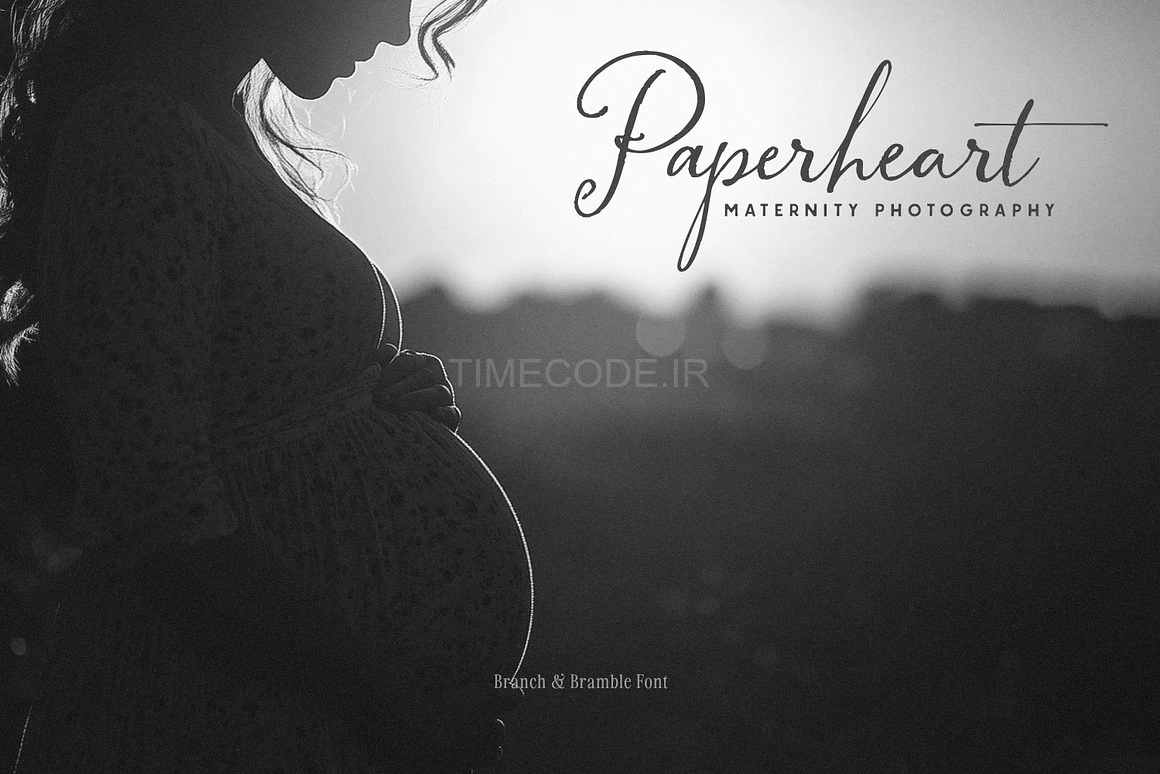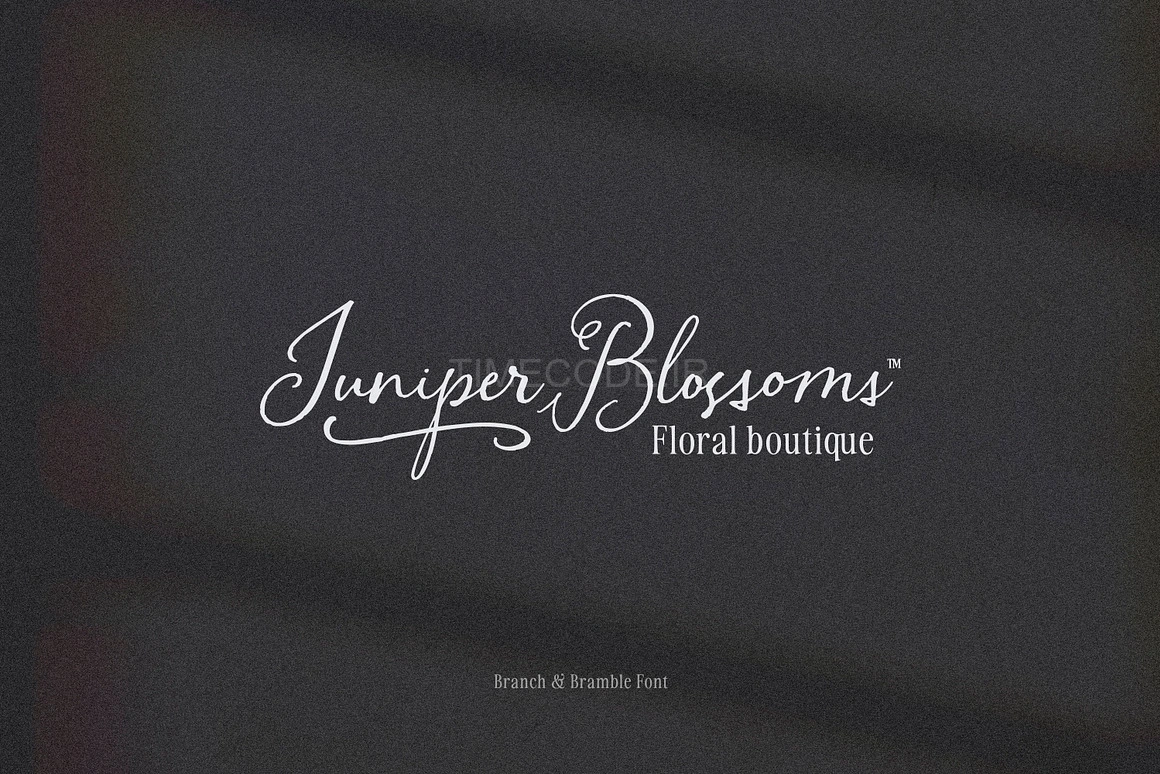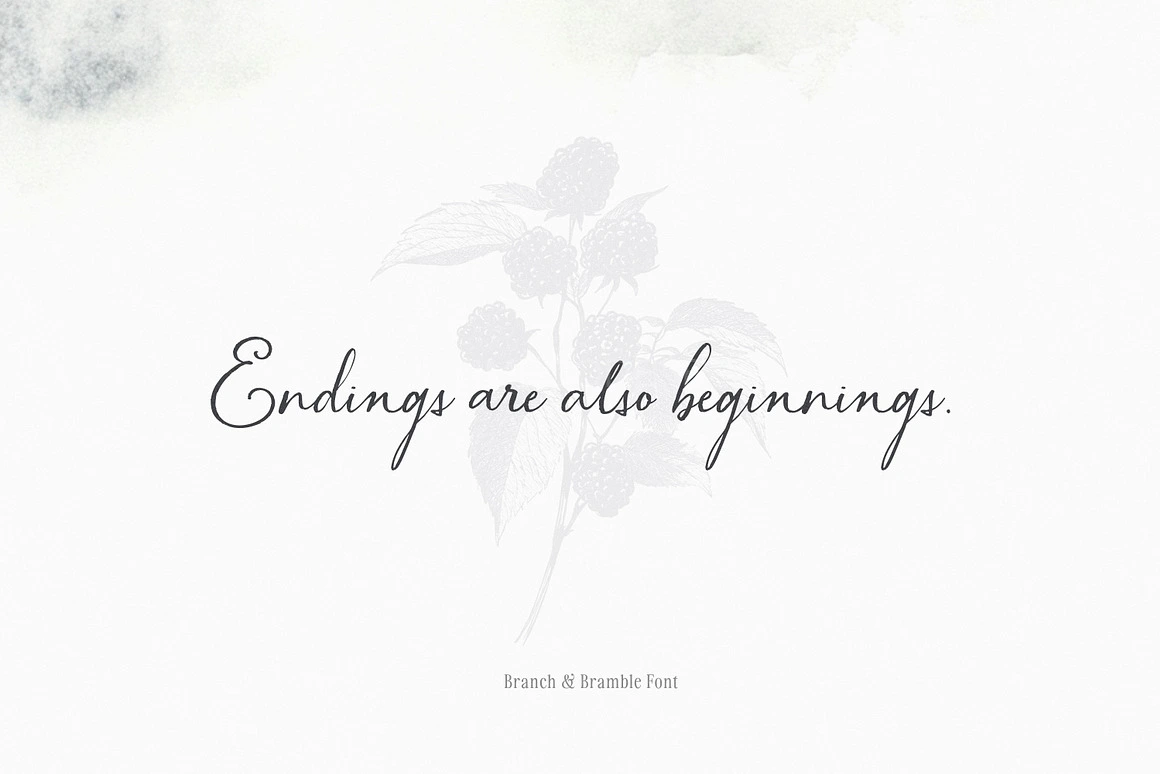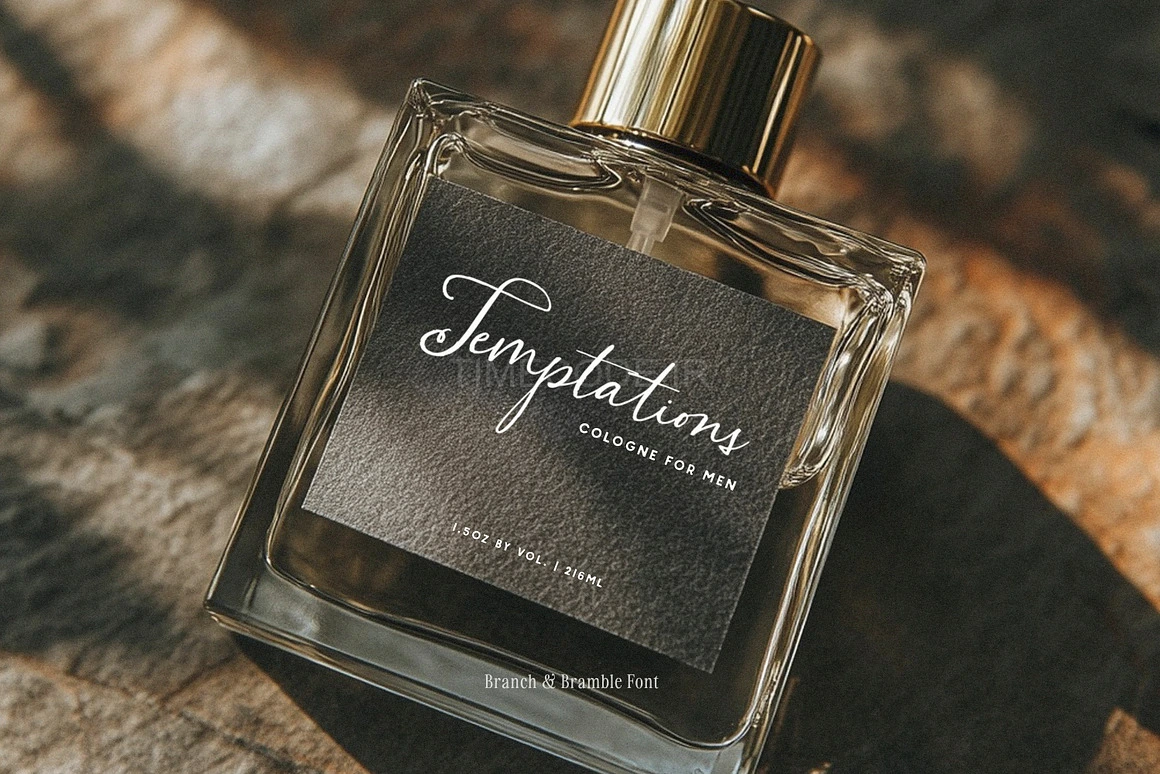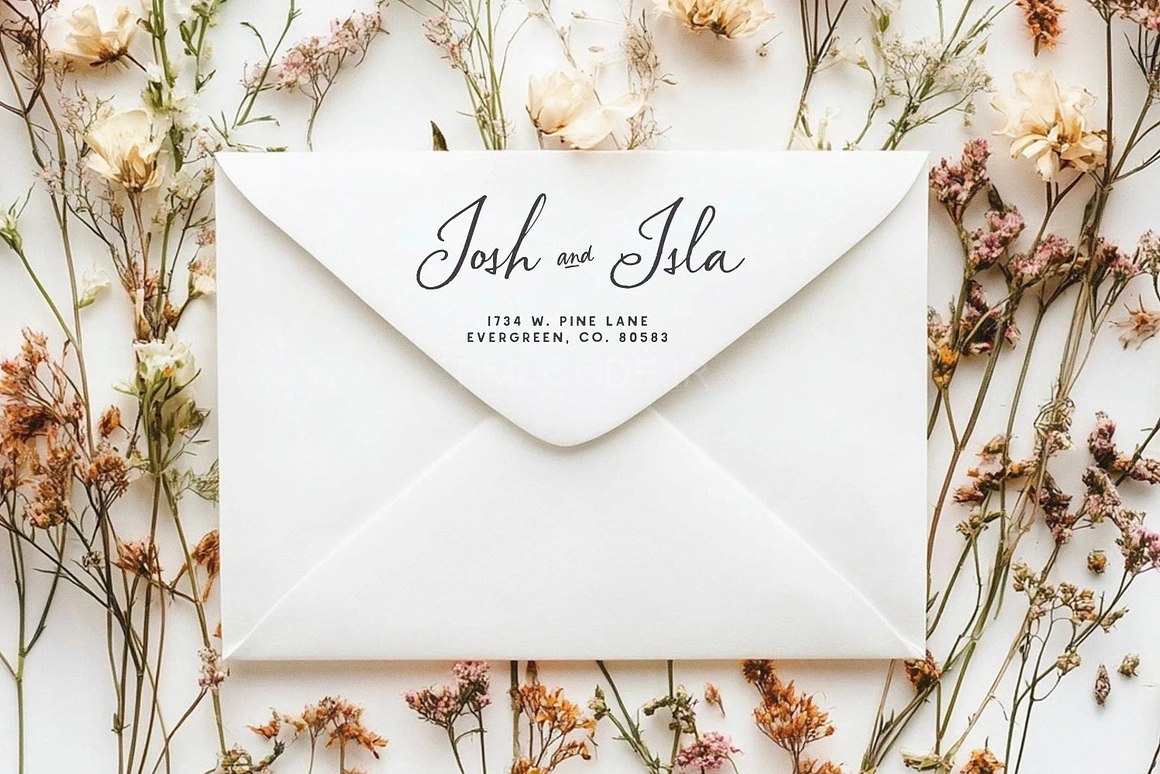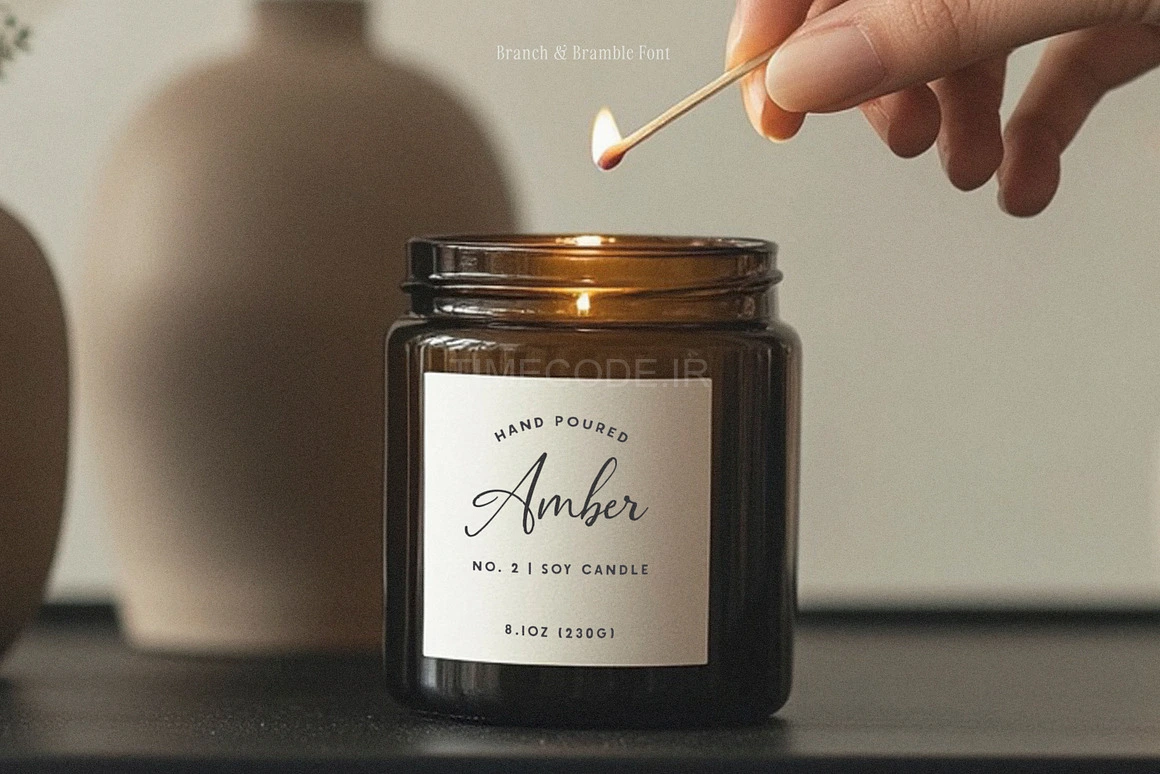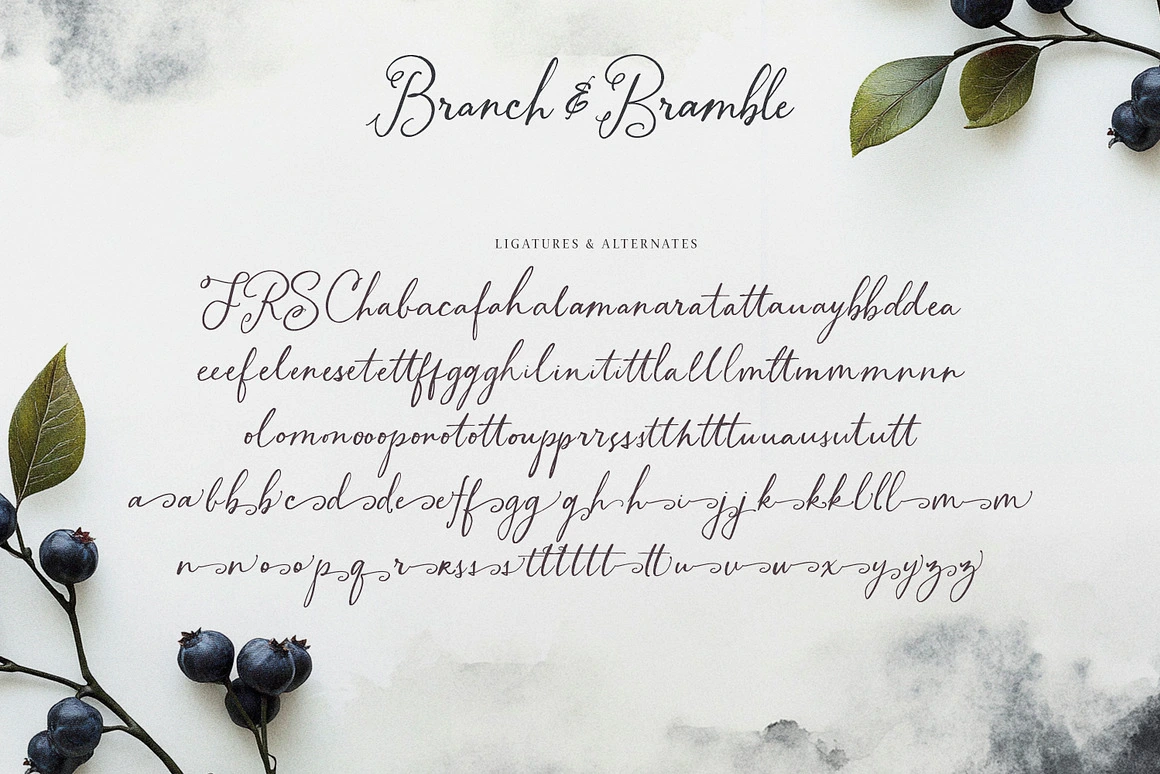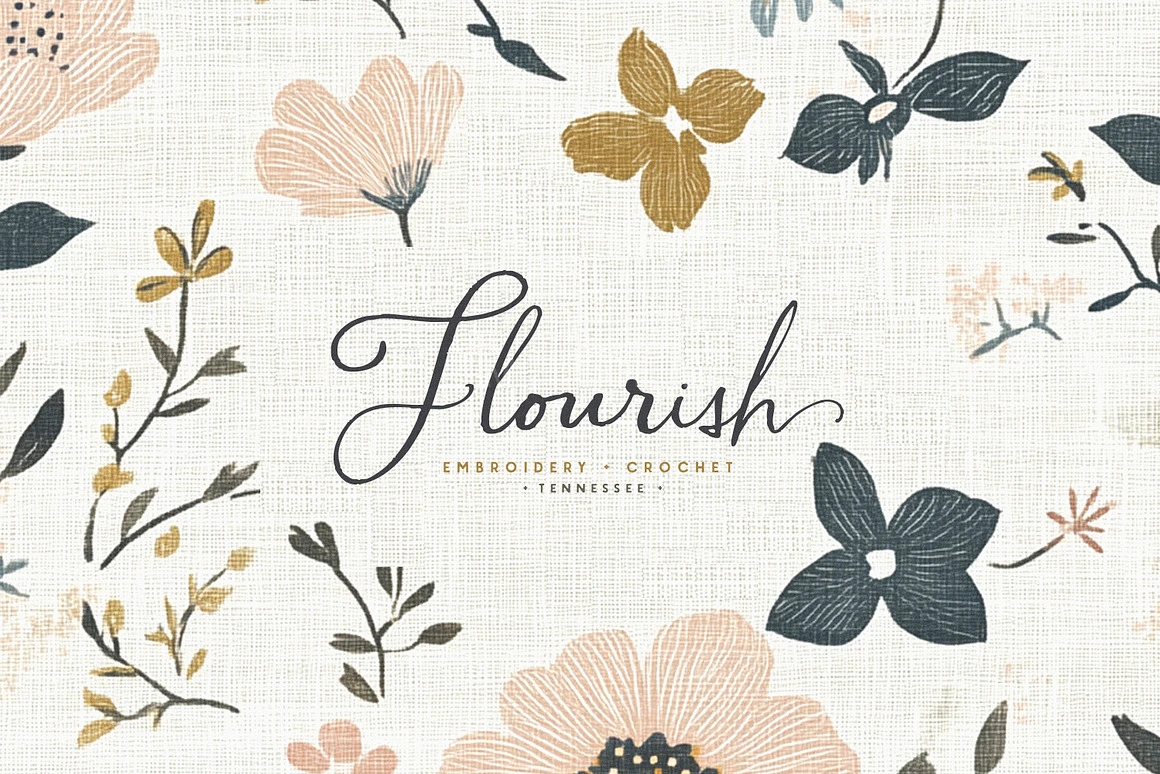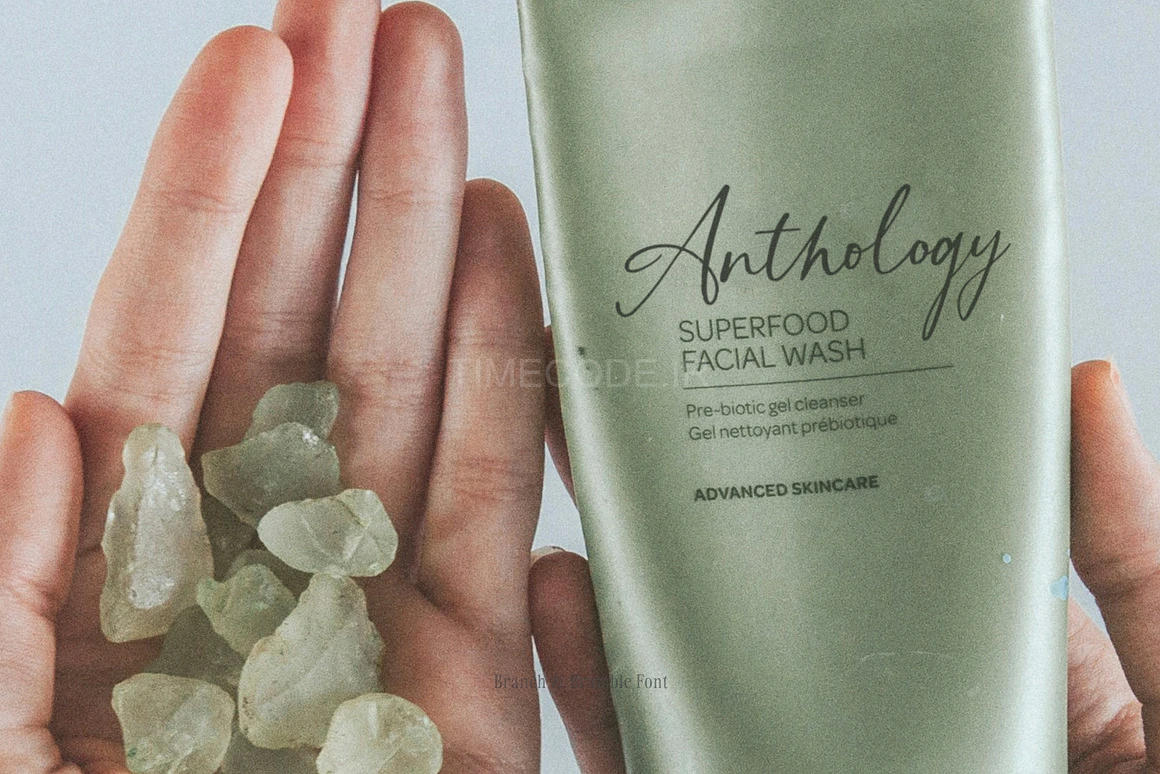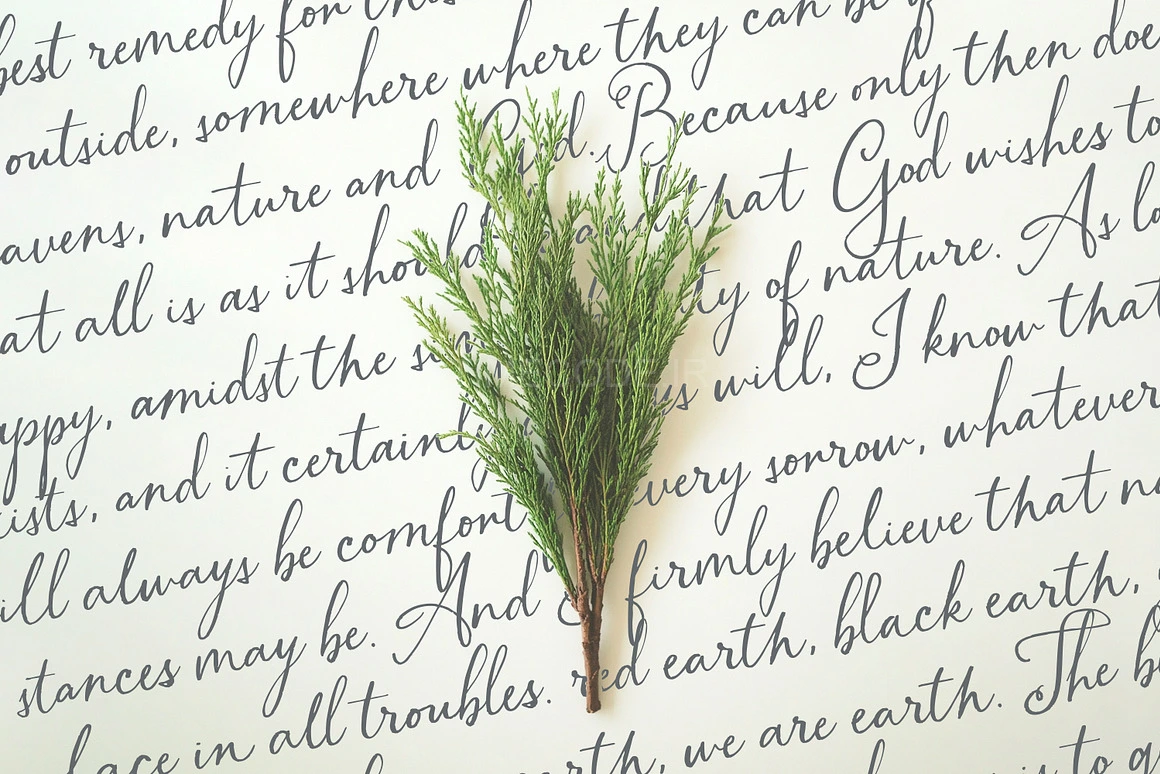
• فونت انگلیسی خوشنویسی شیک
• Branch & Bramble Calligraphy Font
فونت انگلیسی خوشنویسی شیک
این فونت خوشنویسی دست‌نویس دارای یک خط مبنای رقصان، لیگاچرهای ظریف و کاراکترهای انتهایی لطیف برای ایجاد حسی رمانتیک است. این فونت درست به موقع برای فصل عروسی آماده شده است! از آن در دعوتنامه‌ها، کارت‌های Save the Date، جلد کتاب، برندینگ، شعارها، نقل‌قول‌ها و موارد دیگر استفاده کنید! این فونت بسیار دوست‌داشتنی است و من هیجان‌زده‌ام تا ببینم شما با آن چه می‌کنید!
• شامل 130 کاراکتر جایگزین و لیگچر
• لطفاً توجه داشته باشید که این فونت‌ها به صورت دست‌نویس و وکتور هستند، بنابراین لبه‌های آن‌ها عمداً نامنظم است. این فونت‌ها برای استفاده در چاپ/وب بهترین کارایی را دارند، تا استفاده با دستگاه‌های Cricut یا Silhouette
Say hello to Branch & Bramble! I’ve been working on this one for a while, and I’m so happy with how it turned out! This hand drawn calligraphy font boats a dancing baseline, delicate ligatures and delicate end characters for a romantic touch. And it’s ready just in time for wedding season! Use on your invitations, Save the Date cards, book covers, branding, taglines, quotes and more! She’s so lovely and I’m excited to see what you do!
- Including 130 Alternates & Ligatures
- Please Note these fonts are handwritten & vectorized, so the edges are purposely irregular. They are best used on print/web, rather than Cricut or Silhouette.